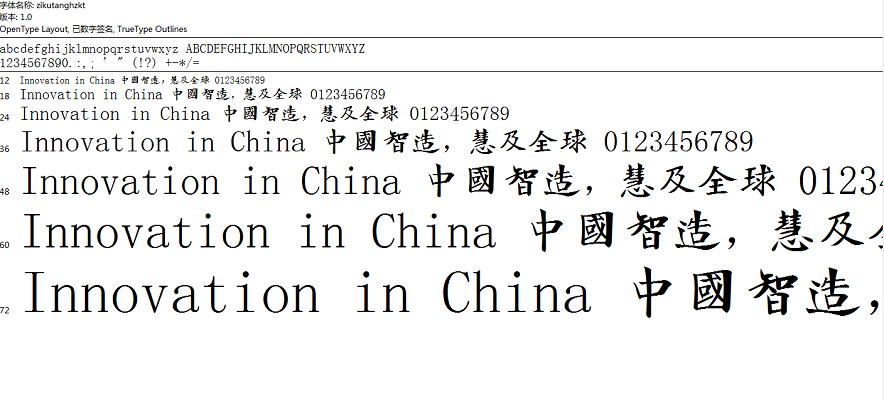
軟件介紹 軟件標簽: 字酷堂 字體 字酷堂海藏楷體一眼望去剛力有勁,給人一種十分精神的感覺,規(guī)整有型,讓人不禁被這款字體所吸引,喜歡這款字體的朋友們快來綠色資源網下載吧!安裝說明:如果您是Win7用戶直接右鍵選擇安裝即可,其他系統(tǒng)的用戶可以將字體文件復制到C:\Windows\Fonts文件夾即可完成安裝相關推薦:字酷堂松風行書 授權:免費軟件 WinAll大?。?.1M語言:中文字酷堂松風行書字體是一種行書字體,該字體清爽流暢,看似隨意卻有其獨特的風格,給人一種流暢的美感,感興趣的朋友們快來下載吧!字體介紹:字酷堂松風行書字體是行書字體的一種,字體書寫流暢,適用于書寫設計字下載地址相關介紹:字酷堂字體制作的底稿多是采用掃描近代書法家的字帖和字跡制作而成,故書法味道挺濃(也正因為此,所以目前字酷堂字體多為繁體字庫,簡入繁出(輸入簡體字直接顯示為繁體))適合用于海報設計、banner設計、包裝設計、古籍排版、網頁設計等方面。 軟件截圖 上一張下一張(1 / 1) 安裝詳細截圖 猜你喜歡 藏文字體軟件 字酷堂字體 藏文字體軟件 藏文字體是根據藏族語言制作的字體,可能使用范圍不是很廣。隨著文化的融合,越來越多的藏文被書寫成了中文字體,所以又稱藏文中文字體,總體效果還是很美觀的。喜歡的朋友,趕快下載體驗吧! 查看更多>> bzdbt藏文字體 1.37M/中文/6.3/下載 字酷堂海藏楷體 1.46M/中文/10.0/免費版下載 喜馬拉雅藏文字體 16.29M/中文/4.4/免費版下載 藏文字體庫大全 5.49M/中文/3.6/76款合集版下載 最全藏文字體合集 1.53M//4.4/共68款下載 字酷堂字體 字酷堂是一個專門致力于書法字體開發(fā)的網站,字酷堂系列字體都是脫胎于書法字體,字體多為繁體字庫,簡入繁出(輸入簡體字直接顯示為繁體),十分適合用于海報設計、古籍排版、包裝設計、banner設計、網頁設計等方面。是一款非常不錯的字體類型,喜歡這一系列字體的朋友們千萬不要錯過哦! 查看更多>> zktqkt 5.52M/中文/5.0/下載 字酷堂黃楷體字體 10.00M/中文/5.0/下載 漢儀字酷堂義山楷字體 10.00M/中文/3.3/下載 zikutangsfxst 2.44M/中文/10.0/下載 zikutanghzkt字體 2.44M/中文/10.0/下載 字酷堂南元松雪行書字體 182.20M/中文/0.9/下載 其他版本下載 標題 大小 更新日期 下載 下載地址 電腦版 字酷堂海藏楷體 免費版 點擊報錯 軟件無法下載或下載后無法使用,請點擊報錯,謝謝! 關閉報錯反饋 請描述您所遇到的錯誤,我們將盡快予以修正,謝謝! *必填項,請輸入內容 本類最新 dreamweaver字體庫 首爾南山體字體 v1.06 官方版 潮字社風云簡ttf 潮字社凌渡鯤鵬簡體字體 潮字社曾玉波手書簡字體 微博慧心字體 相關文章 Photoshop字體安裝使用方法和技巧 如何解決“無法新增字體”問題 Win 7系統(tǒng)安裝字體方法 網頁字體大小設置方法 怎么改網頁字體大小 在Linux系統(tǒng)中安裝字體的幾種方法 windows7字體顯示問題:打開某些程序的時候顯示的是亂碼 用戶評論 熱門評論 最新評論 發(fā)表評論 查看所有評論(0) 昵稱: 請不要評論無意義或臟話,我們所有評論會有人工審核. 字數: 0/500 (您的評論需要經過審核才能顯示)